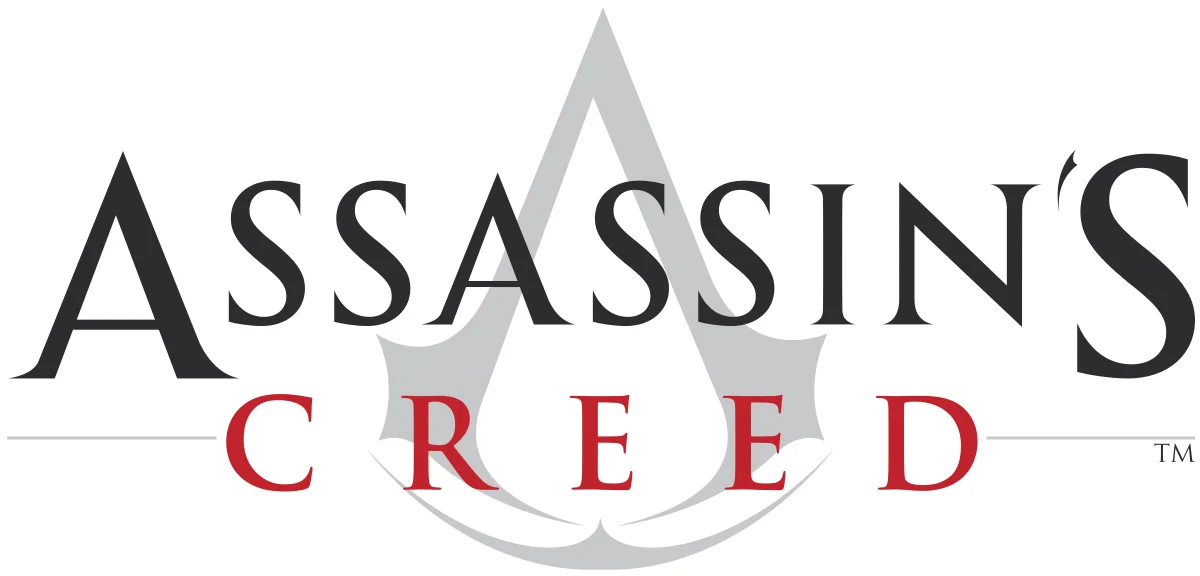
Assassin's Creed Font - Assassin's Creed Font
Assassin's Creed Font
Latin dekoratif yazı tipi P. A. Vannucci tarafından 16 Haziran 2013 tarihinde tasarlanmıştır.
UBISOFT'un en iyi video oyunundan, tüm sevenler için orijinal yazı tipi Assassin's Creed Font